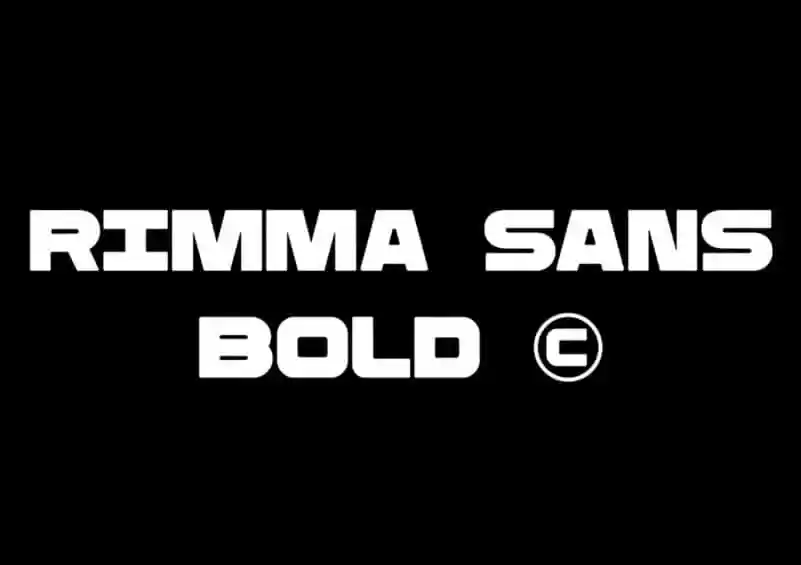
Rimma Bold Sans Serif Font – Download Grátis
Introduzimos a Rimma Bold Sans Serif Font – uma tipografia sans-serif inspirada no uso de estruturas metálicas e fundações de concreto. Essa fonte leva sua força e robustez, oferecendo um design sólido e bold que contrasta com pontuação estreita. A base dessa fonte se relaciona às construções feitas de metal e as fundações de concreto, criando uma ilustração arquitetônica imponente. Combinando os elementos da estética moderna com a elegância do design industrial, Rimma Bold Sans Serif é perfeita para aplicar em marcas esportivas que desejam transmitir força e robustez, combinadas com um toque sofisticado. Esta fonte será uma ótima escolha para aqueles que buscam algo único e poderoso, capaz de criar uma marca atraente e memorável.